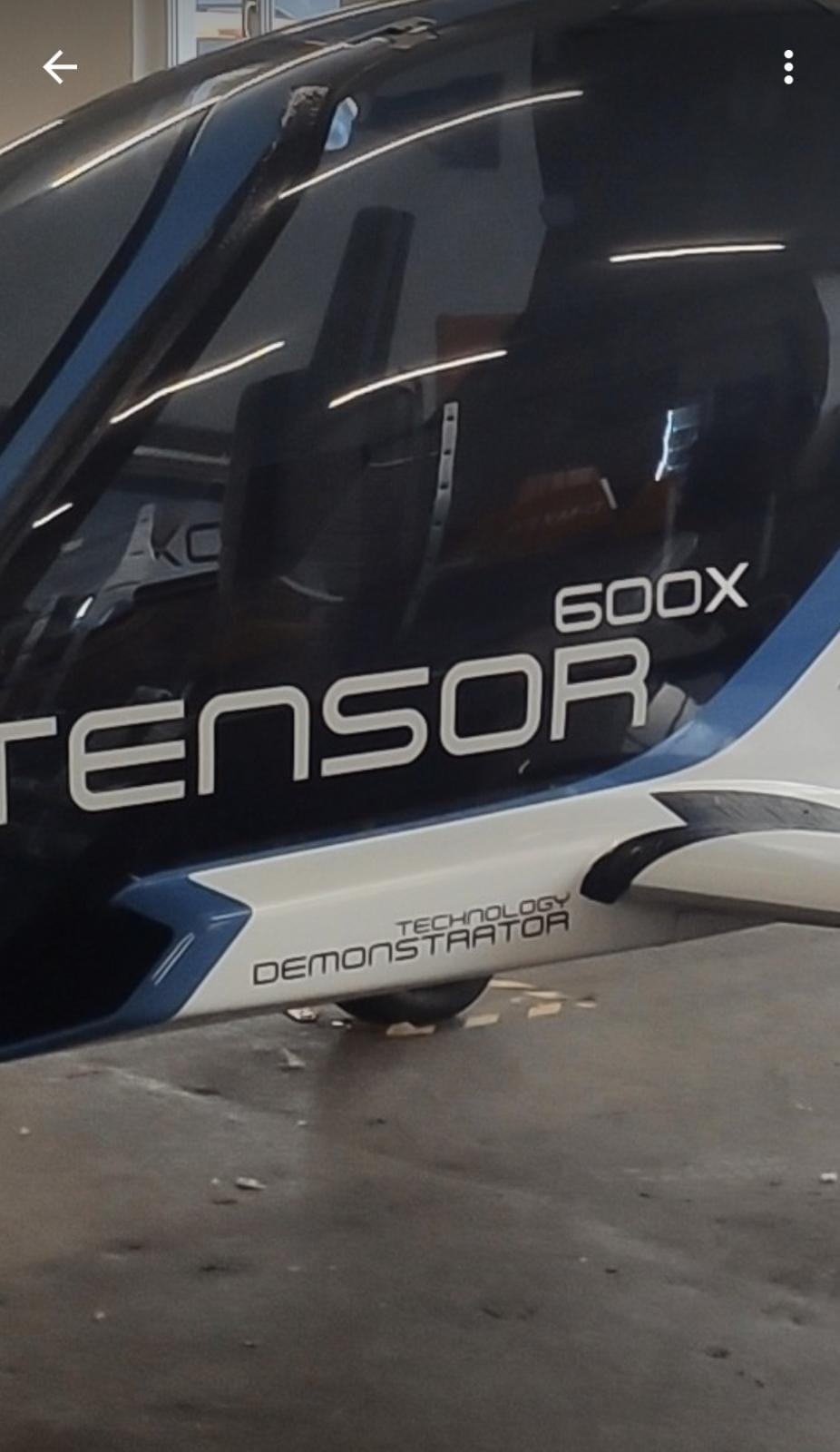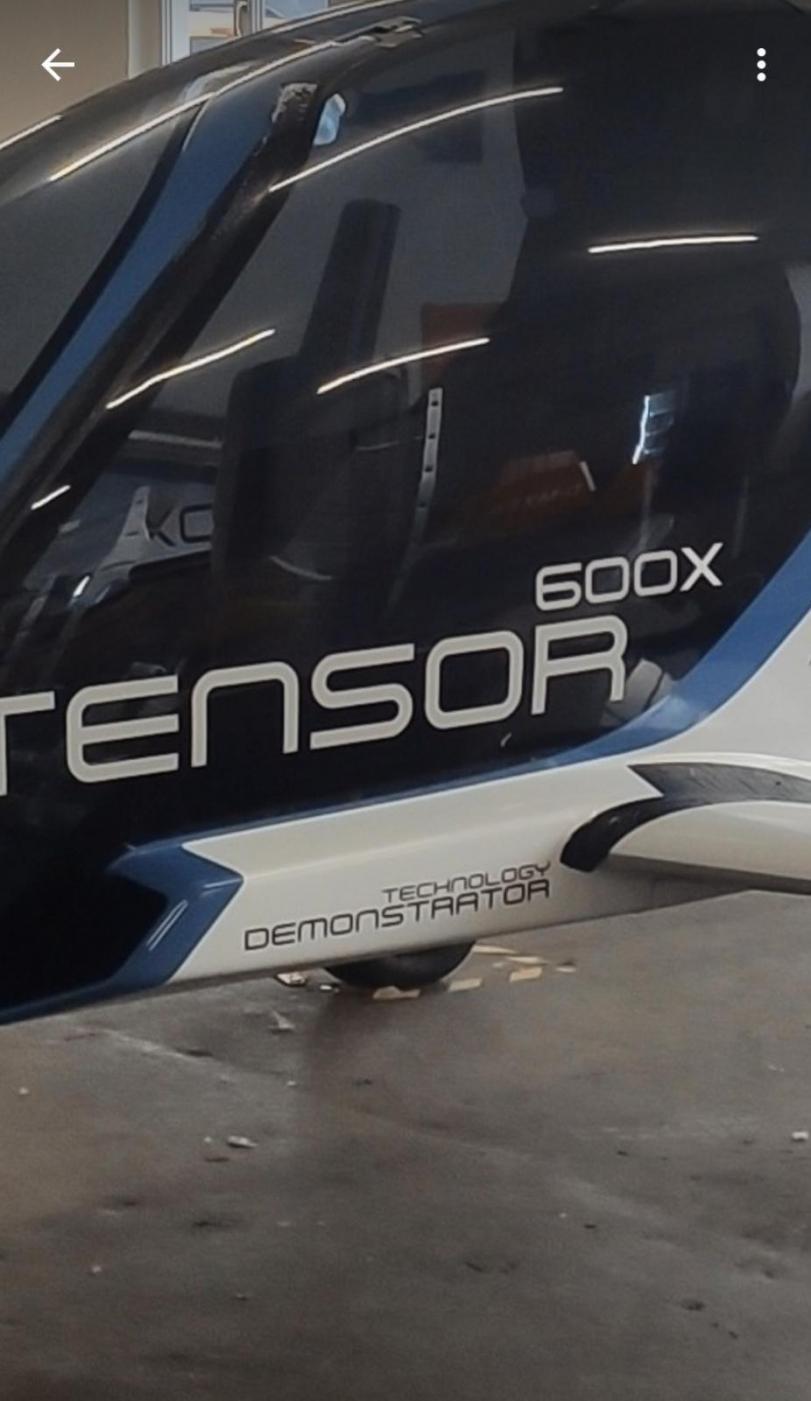
Suche Schriftart, die bei Flugtaxi "TENSOR" verwendet wird
kennt jemand die Schriftart von "TENSOR" auf dem Foto?
ja, darum sagte ich ja 'erinnert'. dafür passt das Kerzenleuchter-Y besser 😉  Controller ist aber näher dran, das stimmt schon. Ich bin mir aber sicher das hier ein fertiger Font Vorlage war, das Logo vom frauenhofer.aero geht ja auch in die Richtung.